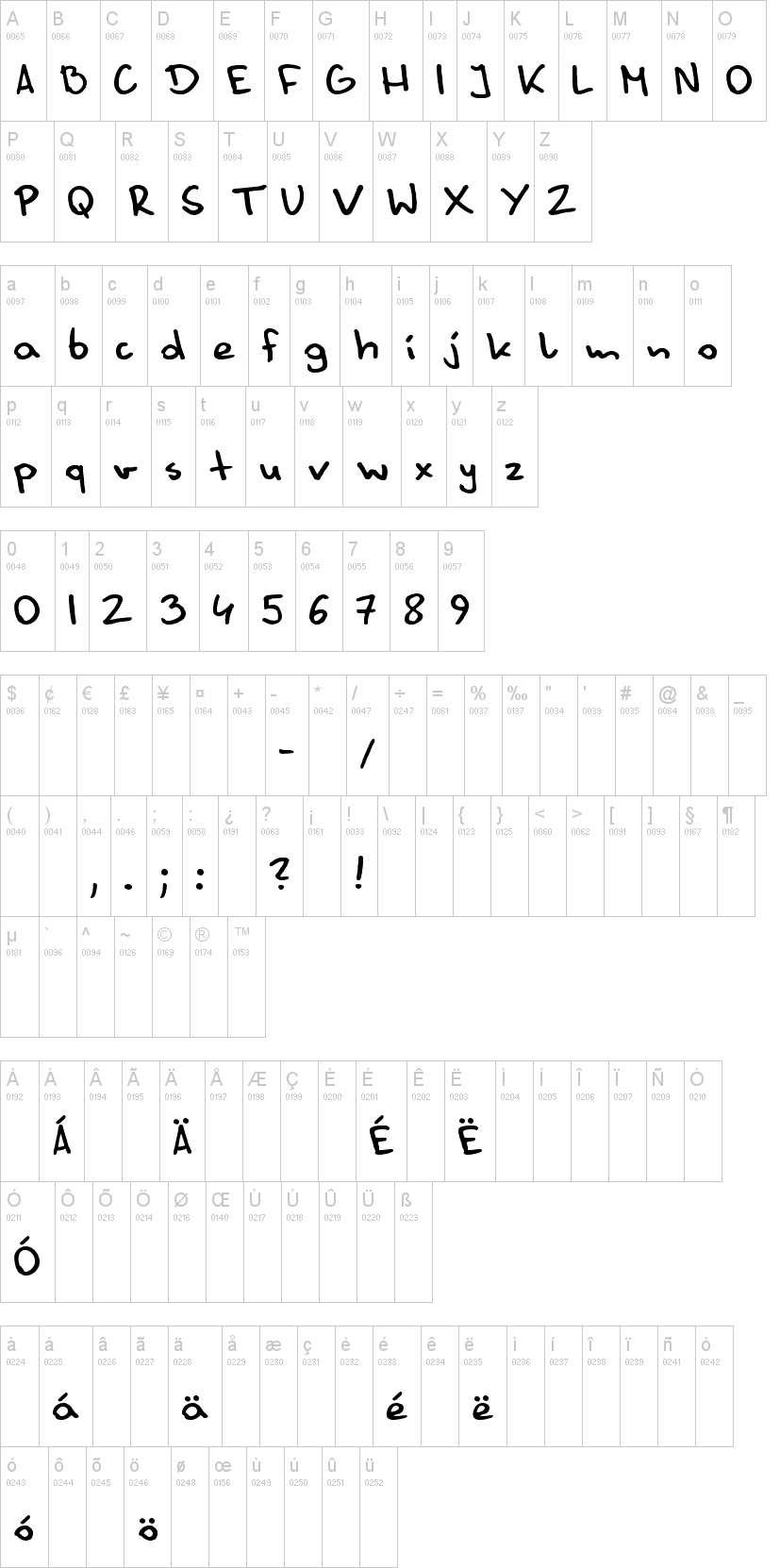
Danny
Danny 字体是一款简约时尚的英文字体,它采用细节优雅的线条,拥有圆润的字母形状,让文字显得更加精致、清晰、优雅。它的设计灵感来自英国设计师 Danny Jones,他把欧洲设计风格和现代风格融合在一起,使得 Danny 字体既有经典的外观,又有现代的视觉效果。Danny 字体适用于品牌标识、海报、字体设计、包装、网站和应用程序等,可以帮助您创造出独特的设计作品。
Danny是一款非常不错的手写艺术字体,具有很好的视觉感,适合于文化类的宣传设计、商业类品牌的广告和产品包装设计以及个性化文字排版等较多场景。
Danny字符映射图